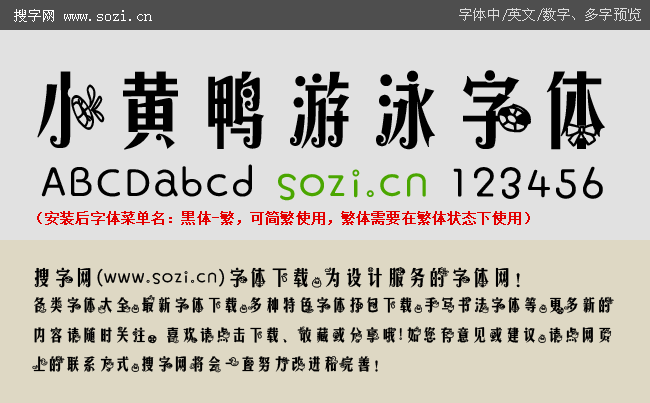
小黃鴨游泳字體
搜字網(wǎng)給大家提供一款小黃鴨游泳字體手機中文字體下載。這款手機字體是在長藝體筆畫間插入了一些卡通圖案。長藝體筆畫既有黑體的粗壯醒目,又有宋體的秀美柔和,加上藝術(shù)性的圓球形點、起筆如蝌蚪形的頓點、螺螄轉(zhuǎn)似的小鉤,配以修長的字形,美觀而不落俗套。加入了卡通圖案后又增添了趣味性,特別適合喜歡手機字體個性一些的朋友在手機上安裝使用。